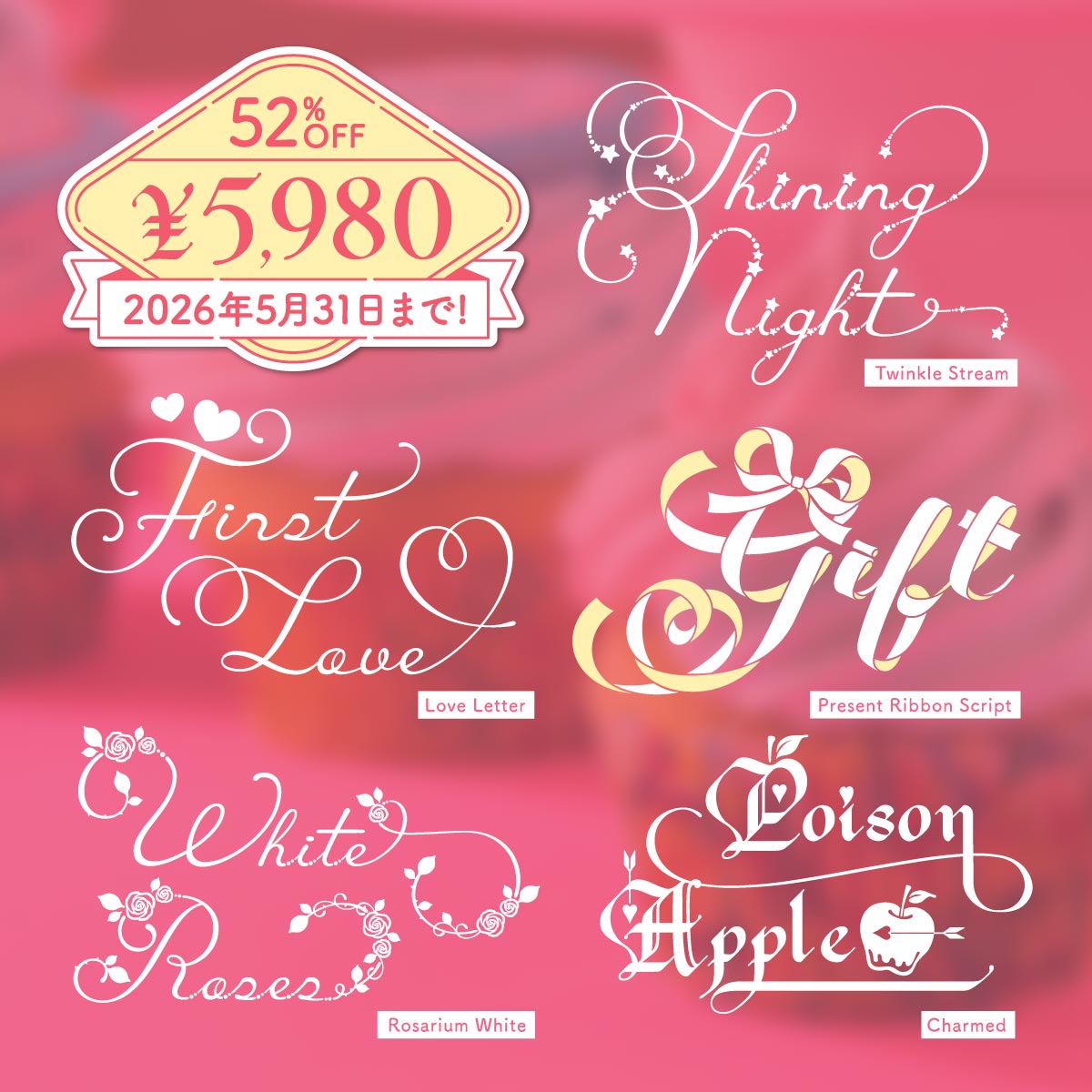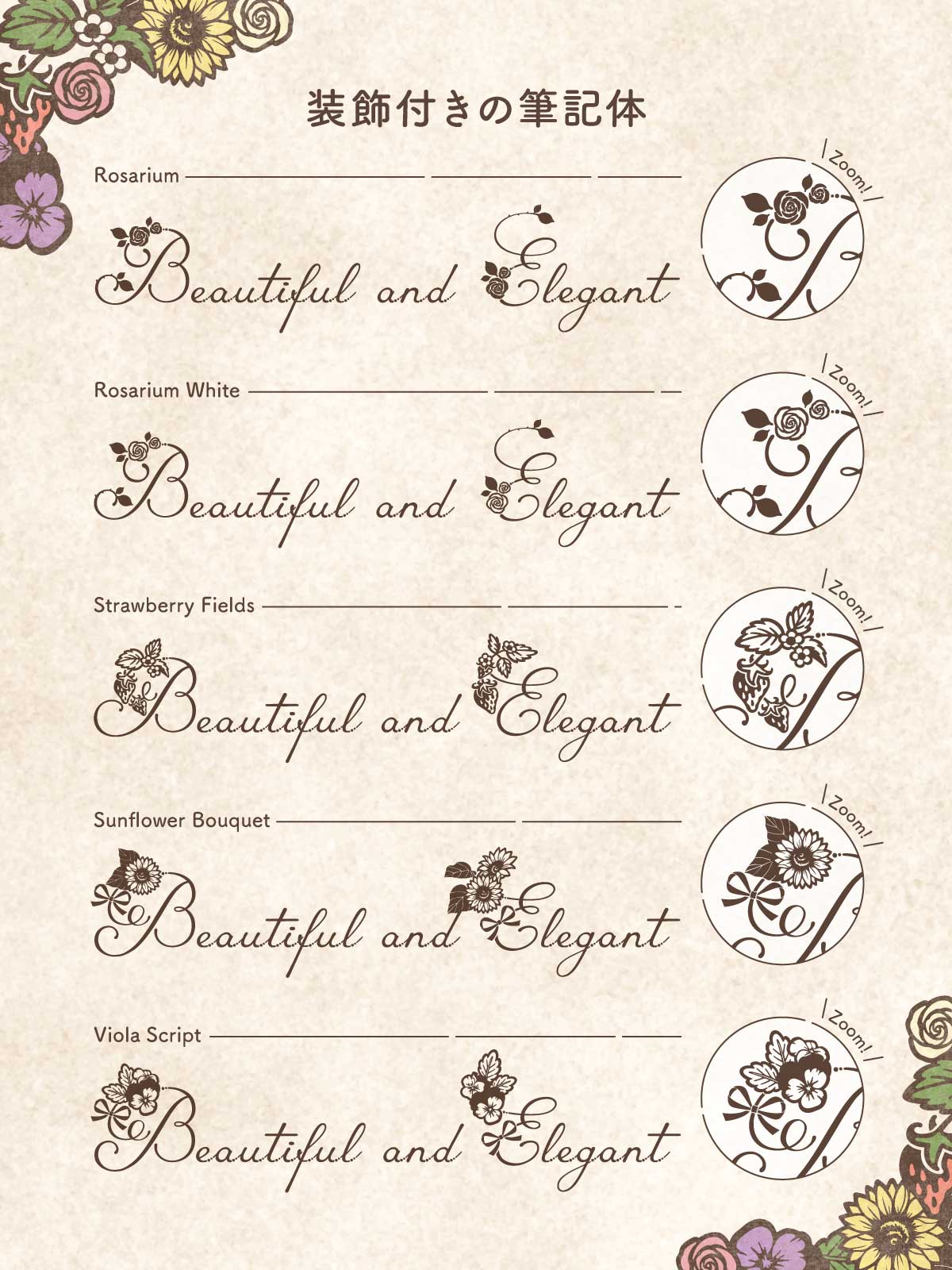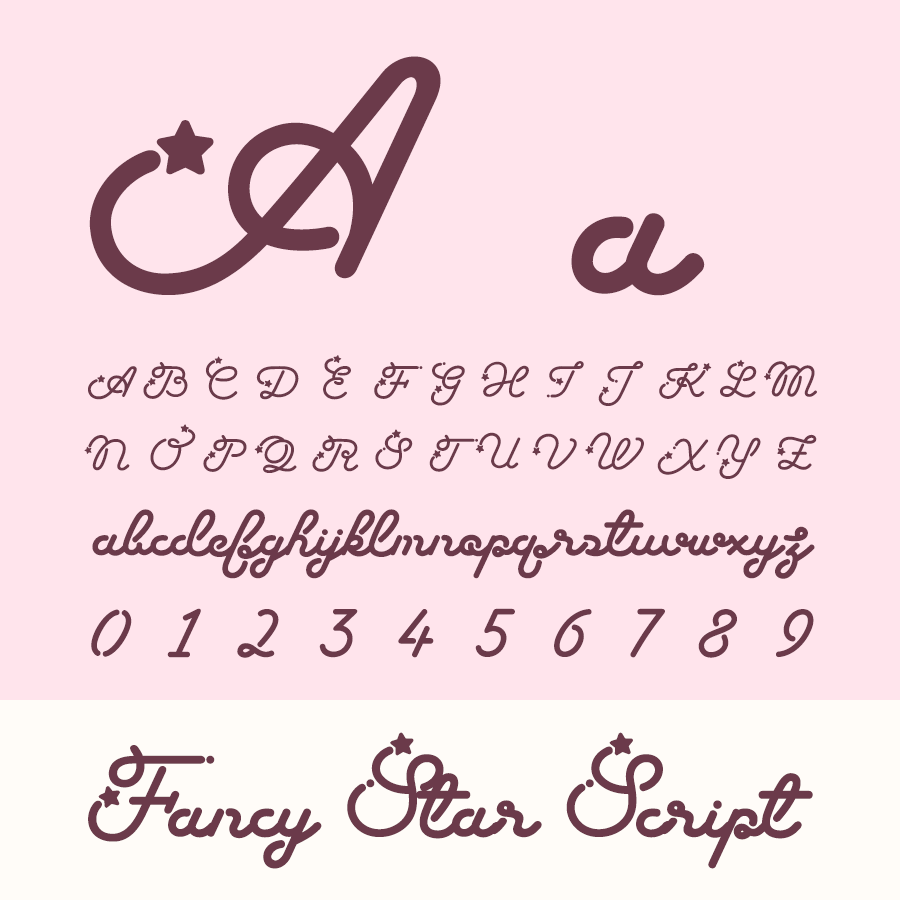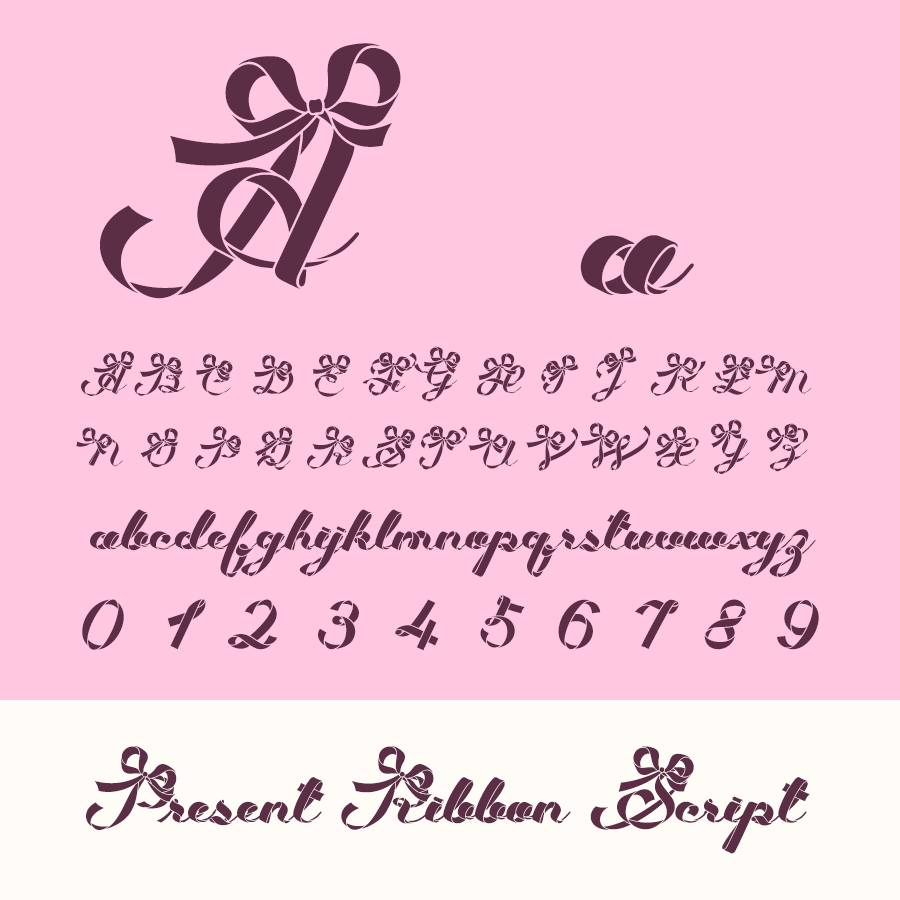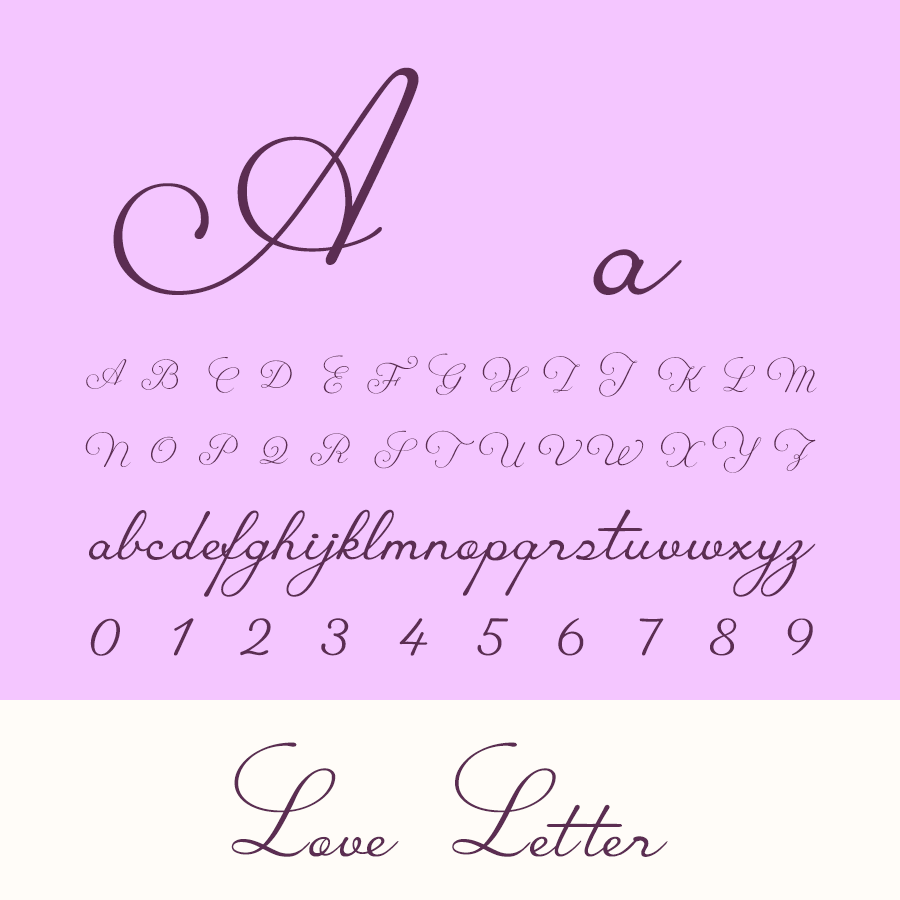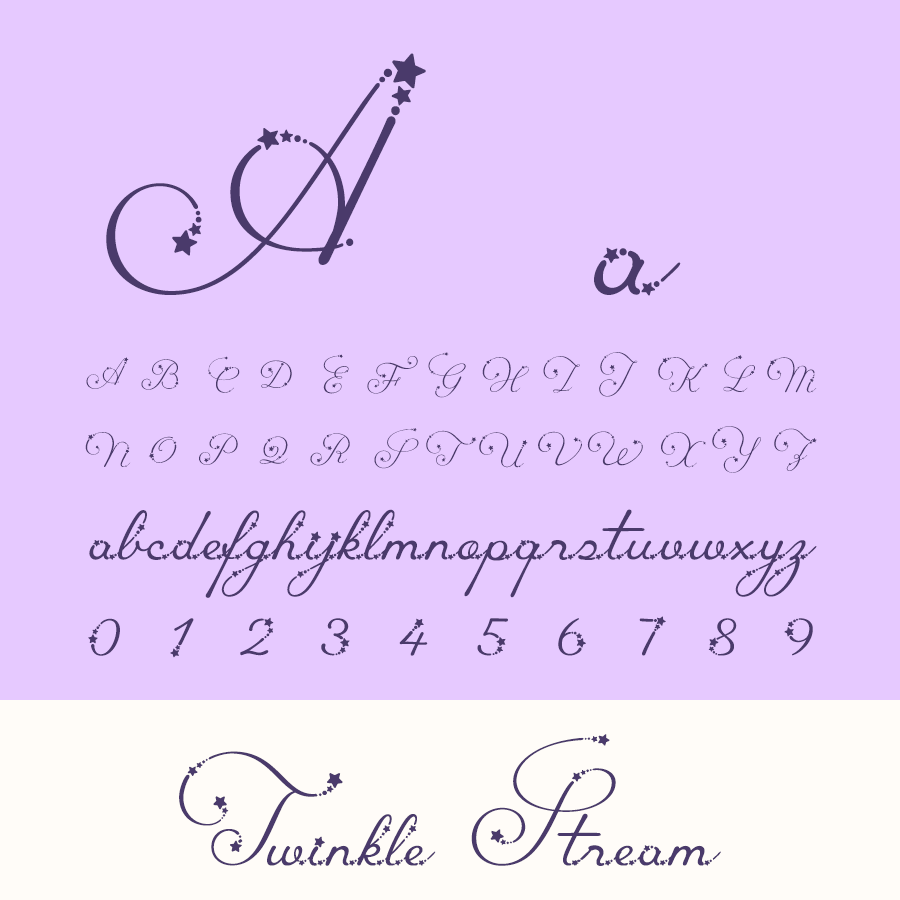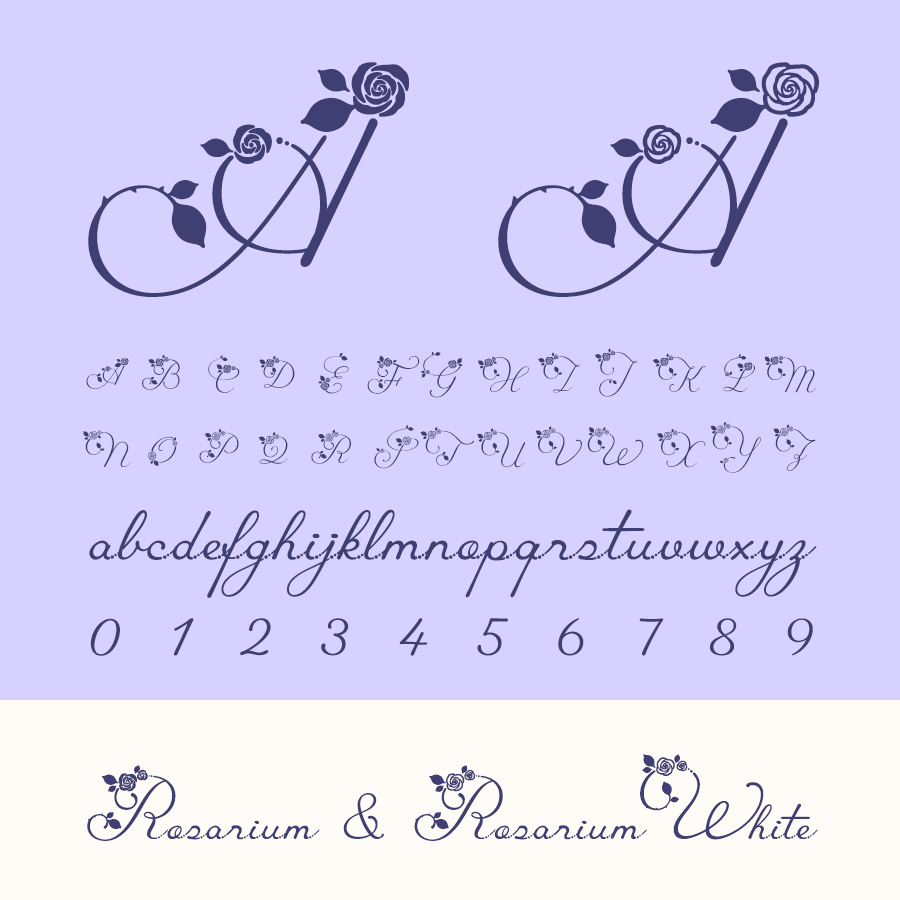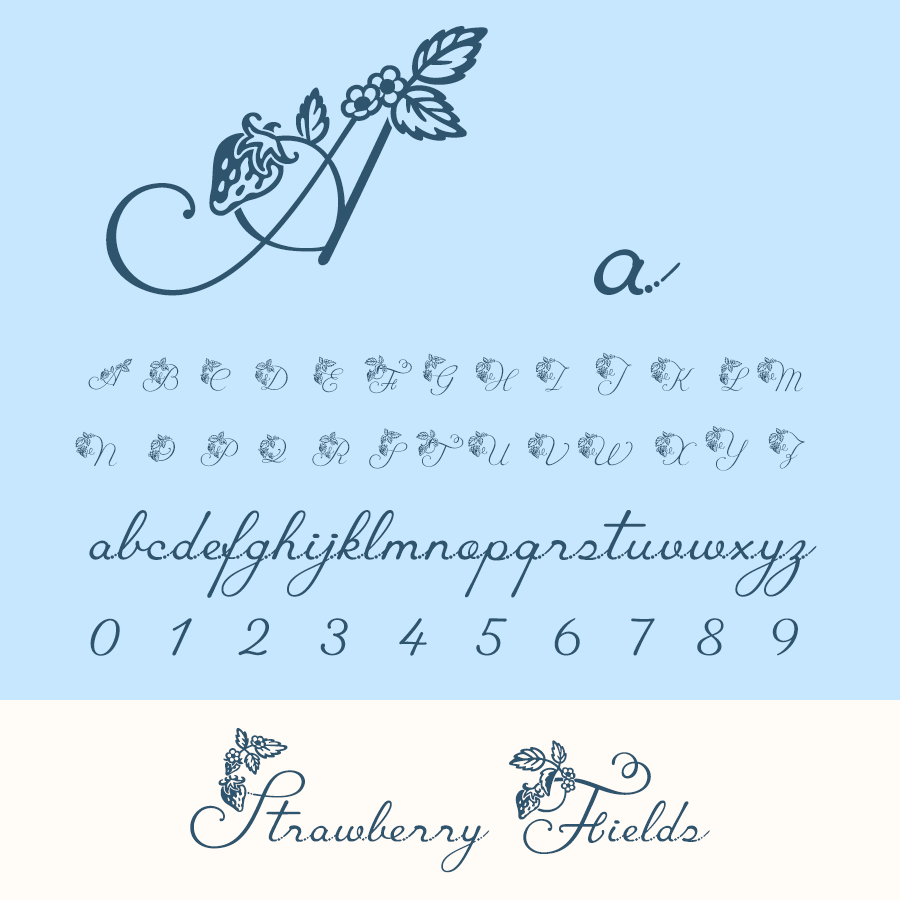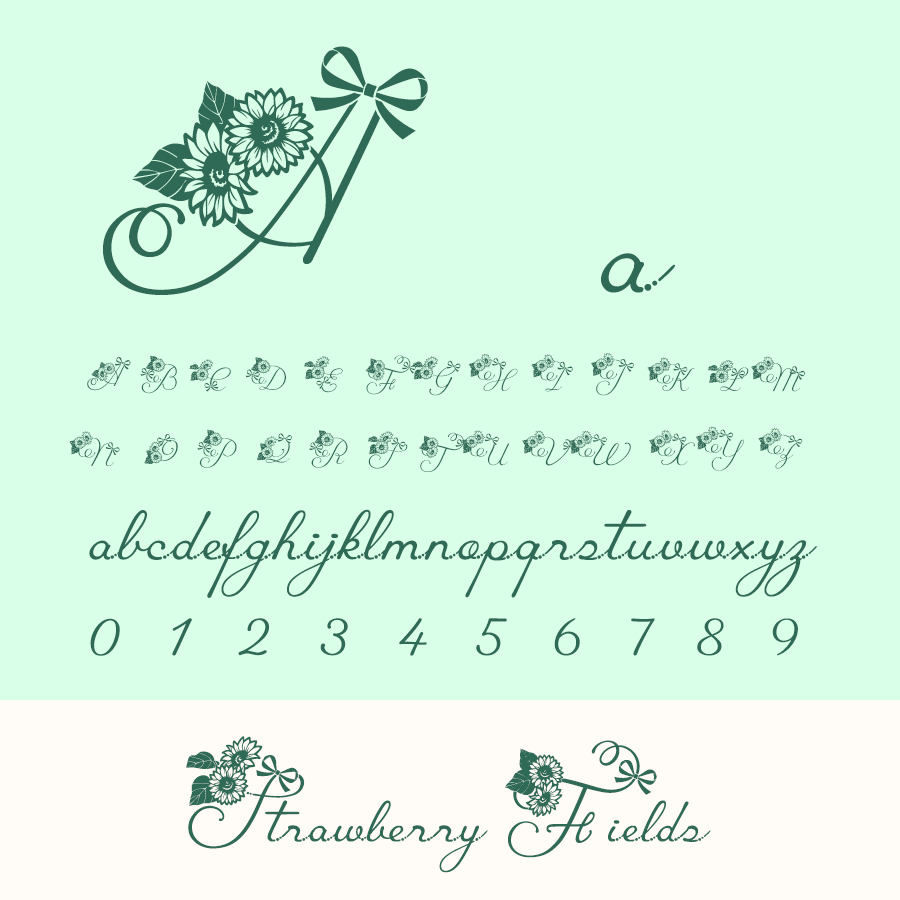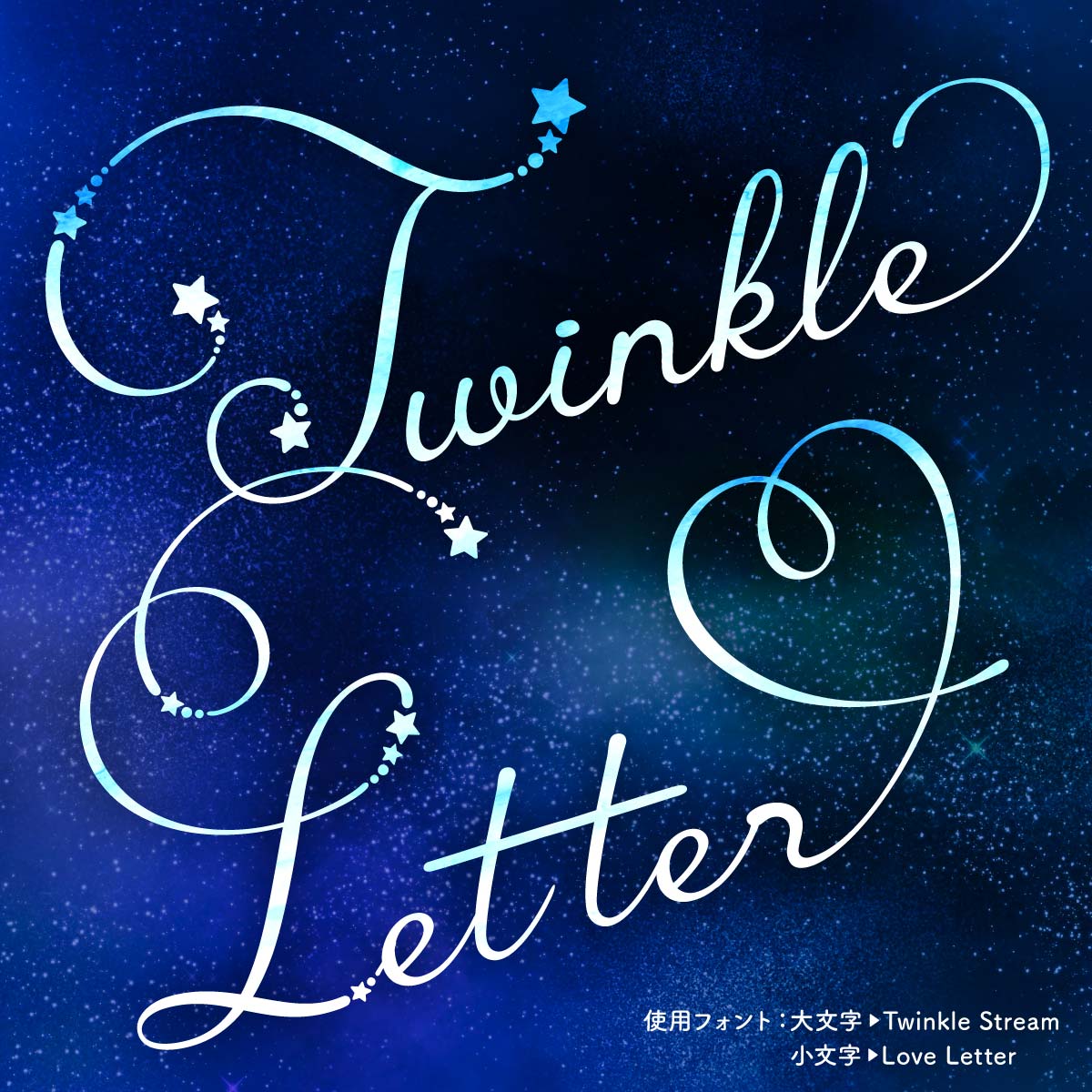
Satsuyakoは、筆記体を中心に、手書き風のあたたかさとデザイン性を兼ね備えた欧文フォントを制作するタイプデザイナーです。
ロゴやSNS投稿、同人誌、ZINEなど「世界観を大切にしたいデザイン」にぴったり。文字を変えるだけで、作品の印象がぐっと変わります。
「Satsuyako」とは
埼玉県在住のフリーランスデザイナー/タイプデザイナー。
「こんなフォントがあったらいいな」という発想から生まれる、シンプルで少し遊び心のあるフォントが特徴です。筆記体やピクセル風などジャンルは多彩で、代表作に「Fancy Star Script」や「Love Letter」などがあります。
カリグラフィーの経験を活かした繊細なデザインと、日本人ならではの感性が織りなす作風は、多くのクリエイターに支持されています。SNSでは制作過程や使い方のヒントも発信中。
「Satsuyako」の特徴
装飾付きの筆記体について
「Rosarium」「Rosarium White」「Strawberry Fields」「Sunflower Bouquet」は、文字の一部に花やフルーツのあしらいが施された装飾付きの筆記体フォントです。
筆記体の中でも、より華やかで印象的なデザインに仕上げることができます。ロゴやカード、パッケージなど、世界観を大切にしたいデザインにおすすめです。
アルファベット・数字・記号まで、豊富な異体字を収録
Satsuyakoのフォントでは、多くのアルファベット・数字・記号に複数のデザイン(異体字)を収録しています。
同じ文字でも少しずつ形が異なるため、作品の雰囲気に合わせて選ぶことができます。文字の組み合わせに変化が生まれることで、より自在に、こなれた印象の作品を仕上げることができます。
異体字とは
漢字の「高」に対し「髙(はしごだか)」があったり、「辻」のしんにょうに1点のものと2点のものがあったりするように、本来同じ音・同じ意味を表す1つの文字に、異なるデザインの文字がある場合、それらを「異体字」と呼びます。
OpenTypeフォントでは、このような異体字を扱うための機能が強化されており、1つのフォントの中に複数の異体字を格納することができるようになりました。Satsuyakoのフォントでもこの機能を活用し、特定の文字をいくつかの異体字に切り替えることができるようになっています。
多彩な異体字デザインへの切り替え例
バリアブルフォントの調整方法
Satsuyako製品の一部は、文字の形状を数値的に変えられる「バリアブルフォント」となっています。
Satsuyakoの筆記体フォントの場合は、この図のように、スワッシュ(装飾的な「はらい」のような筆致)部分の幅や高さを調整できるものが代表例となっています。
※具体的にどのような変形ができるのかは、書体によってまちまちです。変形の性質によっては、文字に応じて変形する部分が限られていたり、そもそも変化する要素がないこともあります。
「Satsuyako」オススメの使い方
VTuber向けのサムネイル
使用フォント:Twinkle Stream、Love Letter
MVやプレイリストのジャケット
使用フォント:Fancy Star Script
ショップカード
使用フォント:Nightingale
「Satsuyako」ラインナップ
個性的で可愛い!豊富な異体字を収録した筆記体
少しレトロでポップな雰囲気が魅力の筆記体 Fancy Star Script
流れるような手書きのラインに、星のモチーフがアクセントとしてあしらわれており、シンプルな文字でも印象的で華やかなデザインに仕上がります。
大文字14種類・小文字17種類の異体字を収録しているため、文字の組み合わせによってさまざまな表情を楽しむことができます。
リボンの装飾があしらわれた華やかな筆記体 Present Ribbon Script
文字の一部にリボンモチーフが組み込まれており、まるでプレゼントを包むラッピングのように、文字そのものがデザインのアクセントになります。
デフォルトの字形に加えて大文字5種類・小文字8種類の異体字が収録されているため、文字の形を組み合わせながら、自分らしい表現を楽しめます。
やわらかく上品な印象のスタンダードな筆記体 Love Letter
流れるような自然なラインが特徴で、ロゴにも長文にも使いやすい、バランスの良いスクリプト体に仕上がっています。
大文字5種類・小文字約20種類の異体字が収録されており、文字の組み合わせによってさまざまなニュアンスを表現できます。
「Love Letter」と組み合わせて使えるフォント
星のきらめきを散りばめた華やかな筆記体 Twinkle Stream
流れるようなスクリプト体に、小さな星の装飾がさりげなく入ることで、文字そのものがデザインのアクセントになります。
大文字5種類・小文字約20種類の異体字を収録しているため、文字の組み合わせによってさまざまな表情を楽しむことができます。
バラ園をイメージしてデザインされた華やかな筆記体 Rosarium
繊細なラインに、バラのモチーフがさりげなくあしらわれており、文字そのものが装飾の役割を果たします。
大文字12種類・小文字約30種類の異体字が収録されているため、文字の組み合わせによってさまざまな表情を楽しむことができます。
苺のモチーフがあしらわれた可愛らしい筆記体 Strawberry Fields
やわらかく流れるスクリプト体に、苺や葉の装飾が加わることで、ナチュラルでやさしい雰囲気を演出できます。
大文字12種類・小文字約20種類の異体字を収録しており、飾りや文字の形を切り替えることができます。
おすすめの使い方
• スイーツ・カフェブランド
• パッケージ・ラベルデザイン
• ハンドメイド・雑貨ブランド
• SNS投稿・ブランドビジュアル
バリアブルフォント対応の筆記体
ひまわりのモチーフが印象的な筆記体 Sunflower Bouquet
やわらかく流れるスクリプト体に、ひまわりの装飾が加わることで、明るく前向きな雰囲気を演出できます。
大文字11種類・小文字約20種類の異体字が収録されており、文字の形や装飾を切り替えることができます。
バリアブルフォントに対応した環境では、文字の形を微調整することでより自然な文字組みに仕上げることができます。
文字がセーターのような編み柄で表現されており、見た瞬間にあたたかみを感じられるデザインが魅力です。
アルファベット・数字・記号に加えて、50種類以上の絵文字や装飾パーツが収録されているため、文字だけでなくデザイン素材としても活用できます。
おすすめの使い方
• 冬シーズンのデザイン
• SNS投稿・バナー
• キッズ・かわいいデザイン
• パッケージ・ショップツール